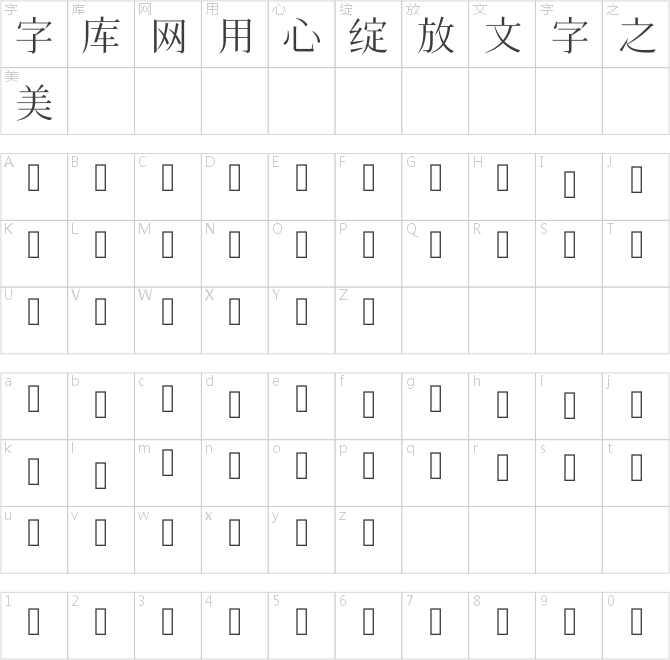
花园明朝
花园明朝介绍
日本花园明朝体在免费字体中算是非常非常好的一款了,花园明朝 (Hanazono) 是一个免费字体,为 GlyphWiki 所研发,字形数量共 45090 + 47186 个,几乎收录了所有汉字字形(但看起来没有区分不同地区标准字形)。 一共收录了八万多汉字的免费字体,本次发布的是八万汉字完整版。 第一步这个字体的轮廓是用 CHISE 计划的影系统生成的,数据来源就是 Glyphwiki,因此可以在相对短的时间内生成N多的文字(貌似今年刚补完日本的户籍统一文字),但是影系统生成的笔画轮廓实在是不敢恭维,其避让系统也不算很完善,不能用来生成很粗的字。